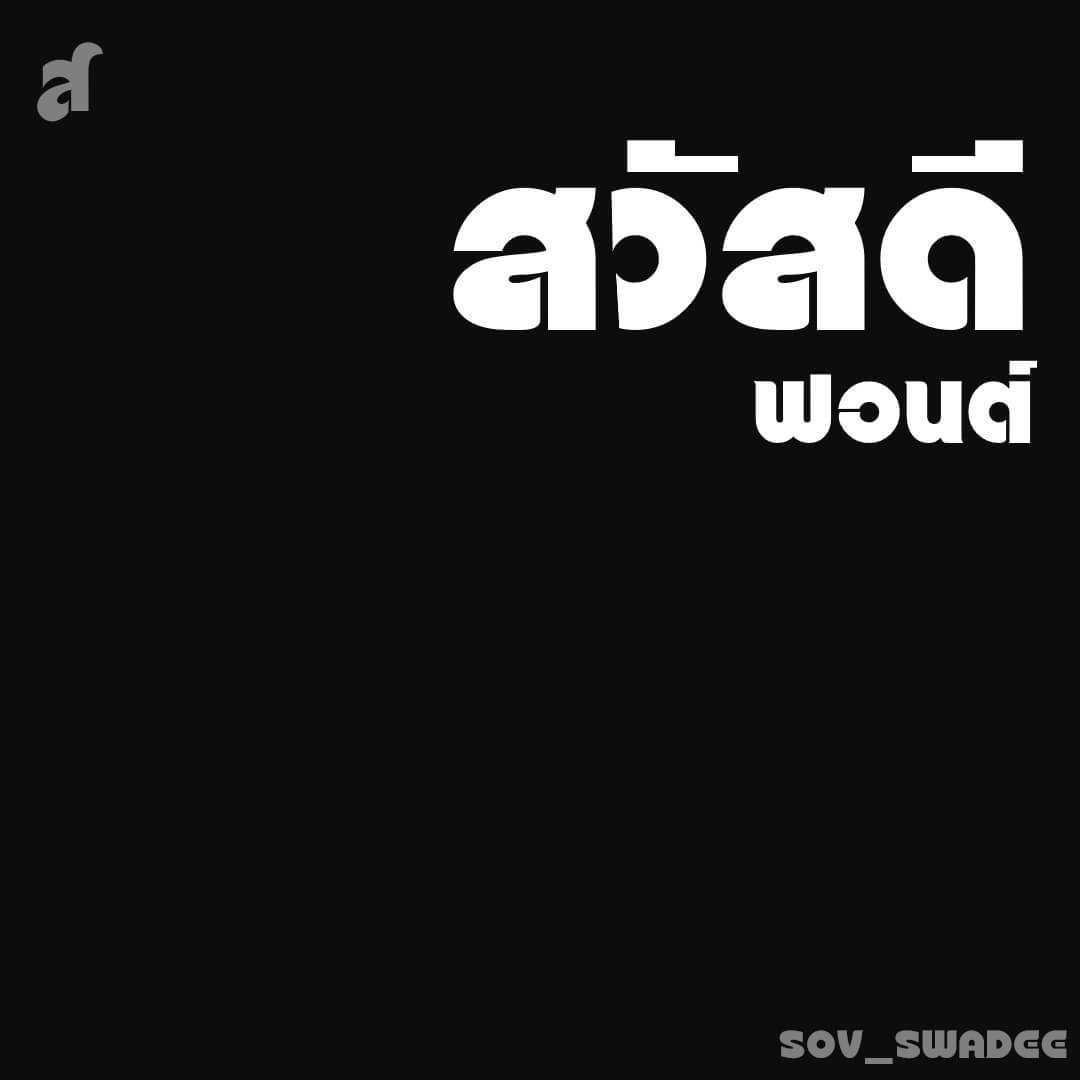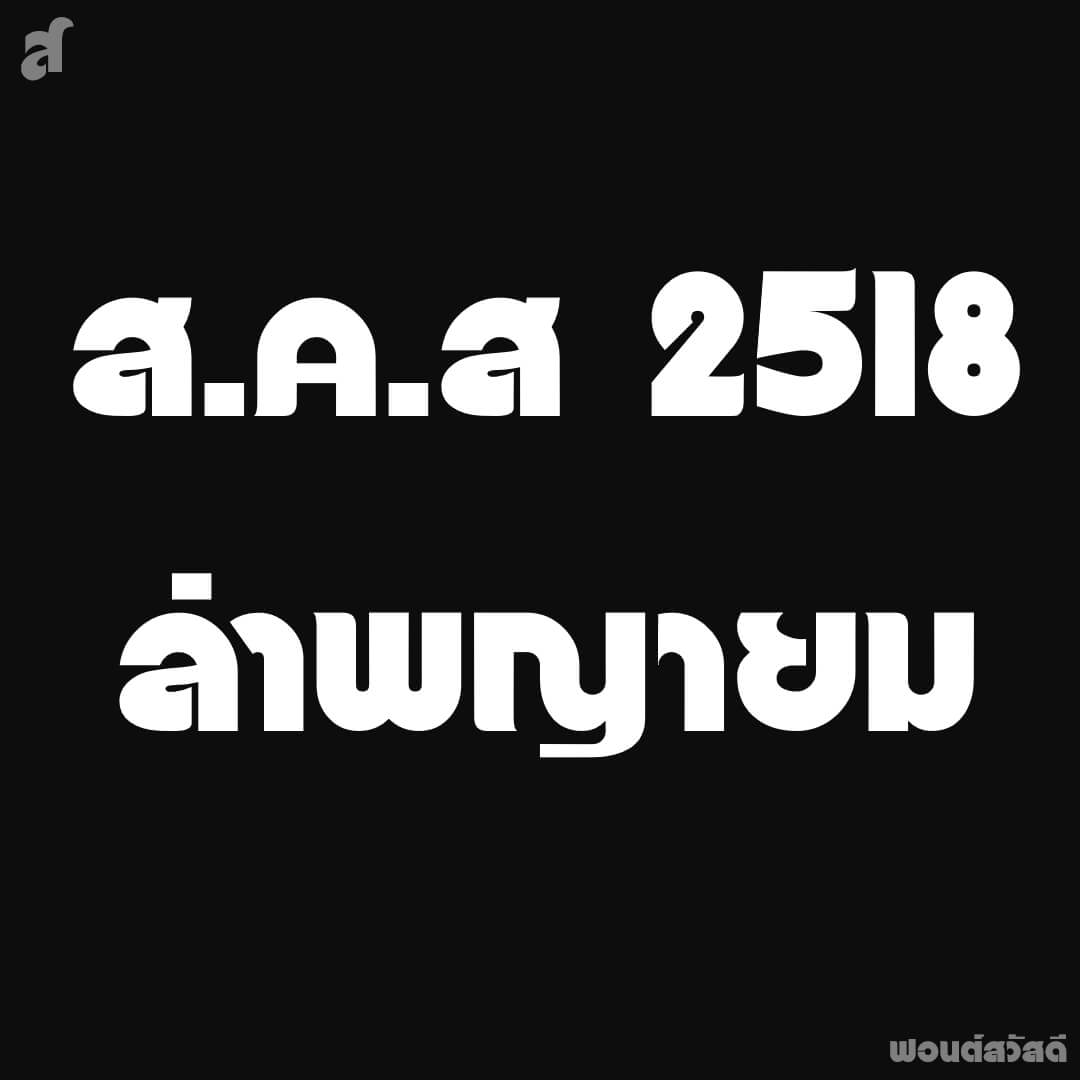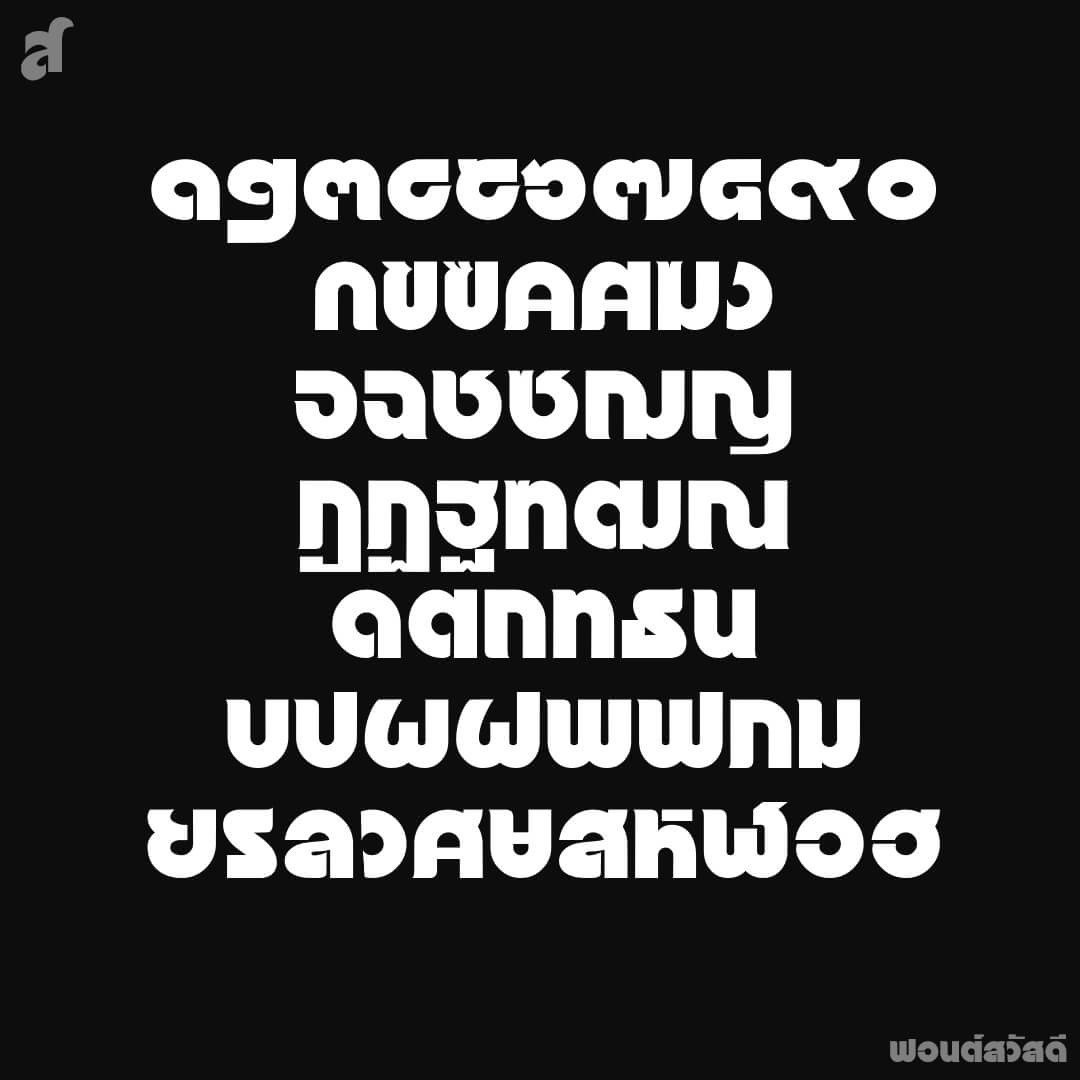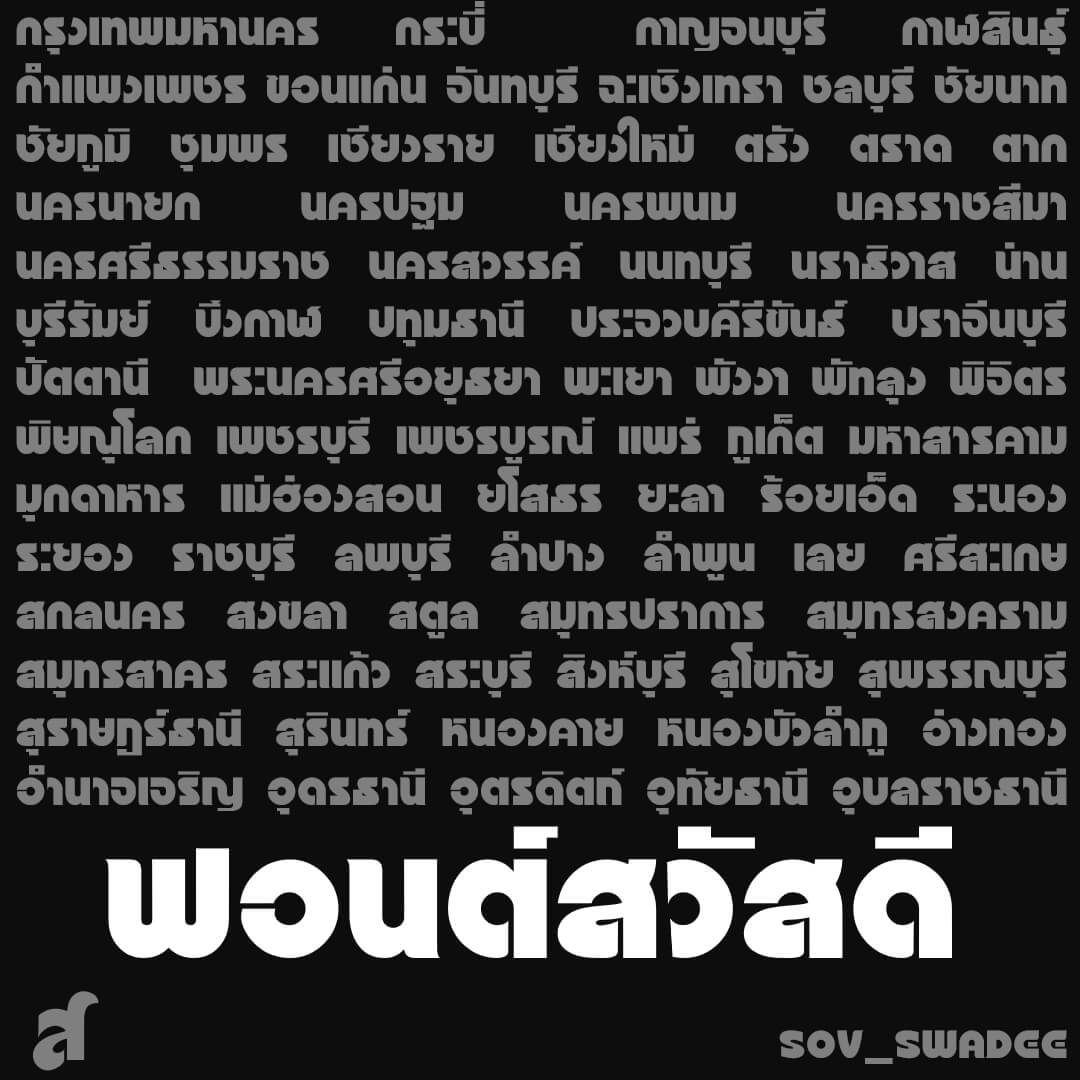
ฟอนต์สนทนา – ที่มาจากโฆษณาภาพยนตร์ ล่าพญายม ในหนังสือพิมพ์ ต้นปี ๒๕๑๘ อักษรไม่มีหัวตัวกลมบ็อก เมื่อกว่า 50 ปีที่แล้ว… แอบสะบัดปลายน้อยๆ เพิ่มเข้าไปหน่อยนึงเน่อ
เบื้องหลังการออกแบบ : ฟอนต์ สวัสดี
สวัสดี (SOV_Swadee)